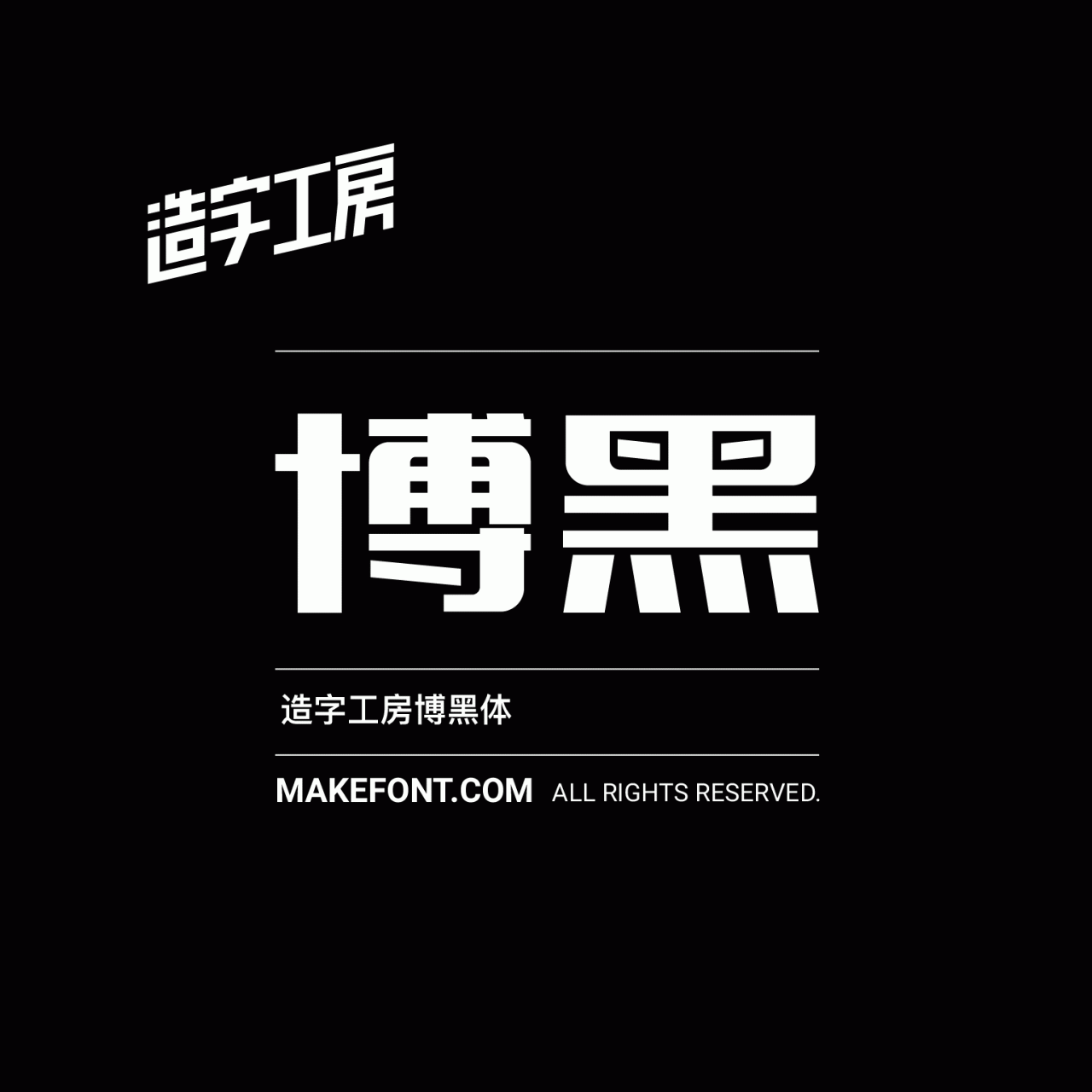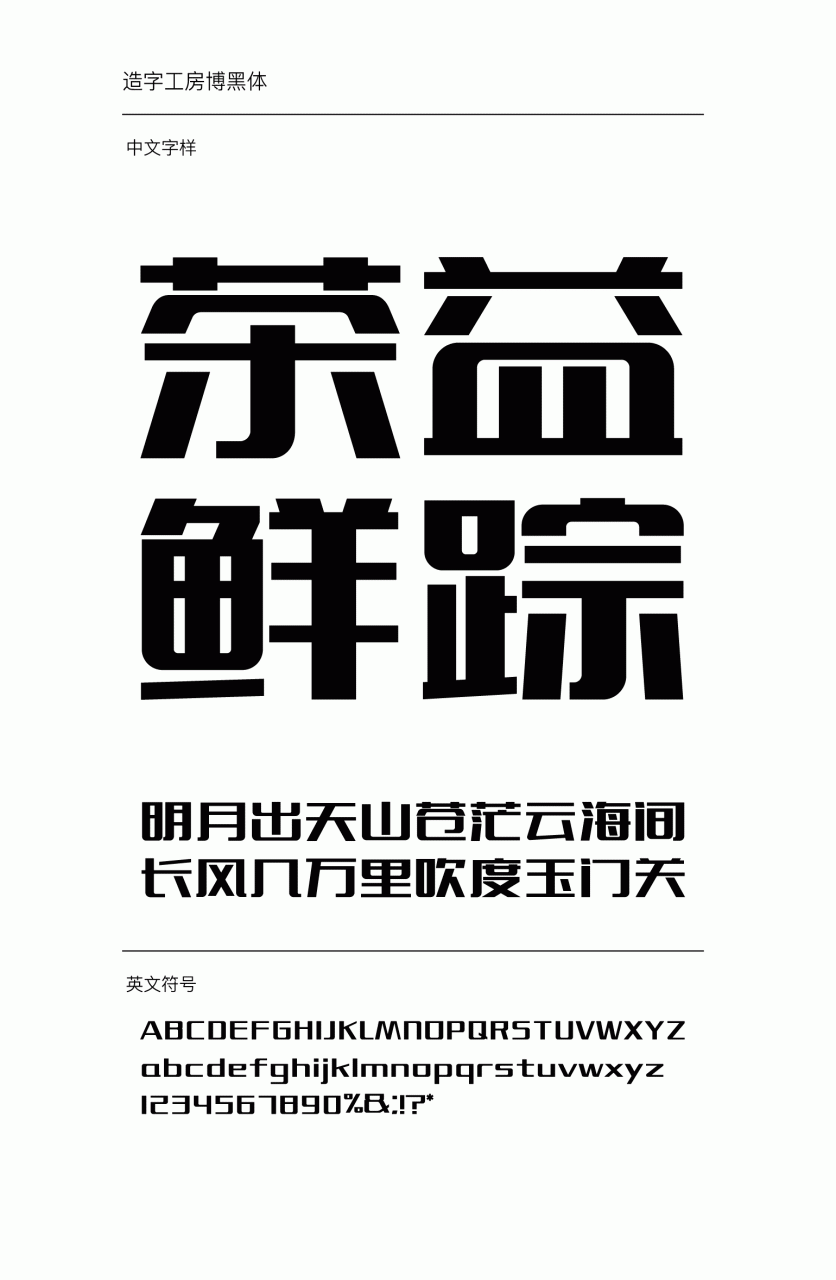
造字工房博黑常规体设计说明
造字工房博黑体,整体字形风格厚重沉稳、制作采用偏上的中宫方式,使其字形方挺规整,主副笔画处理清晰明确,笔画大小极变、轻重有节、直角和圆角处理穿插,刚柔并济,有沉稳雍容的静意之美,具有极强的时尚感。此款字体适用于文字标题、广告设计、企业宣传及时尚品牌的设计应用,有着极强的应用空间。 本字体为简体字库,采用OpenType/CID格式,Adobe-GB1-5编码。基于中华人民共和国GB2312-80字符集标准,另按需添加101个汉字。共收容字数6864CJK汉字,ASCII常用字符100个。